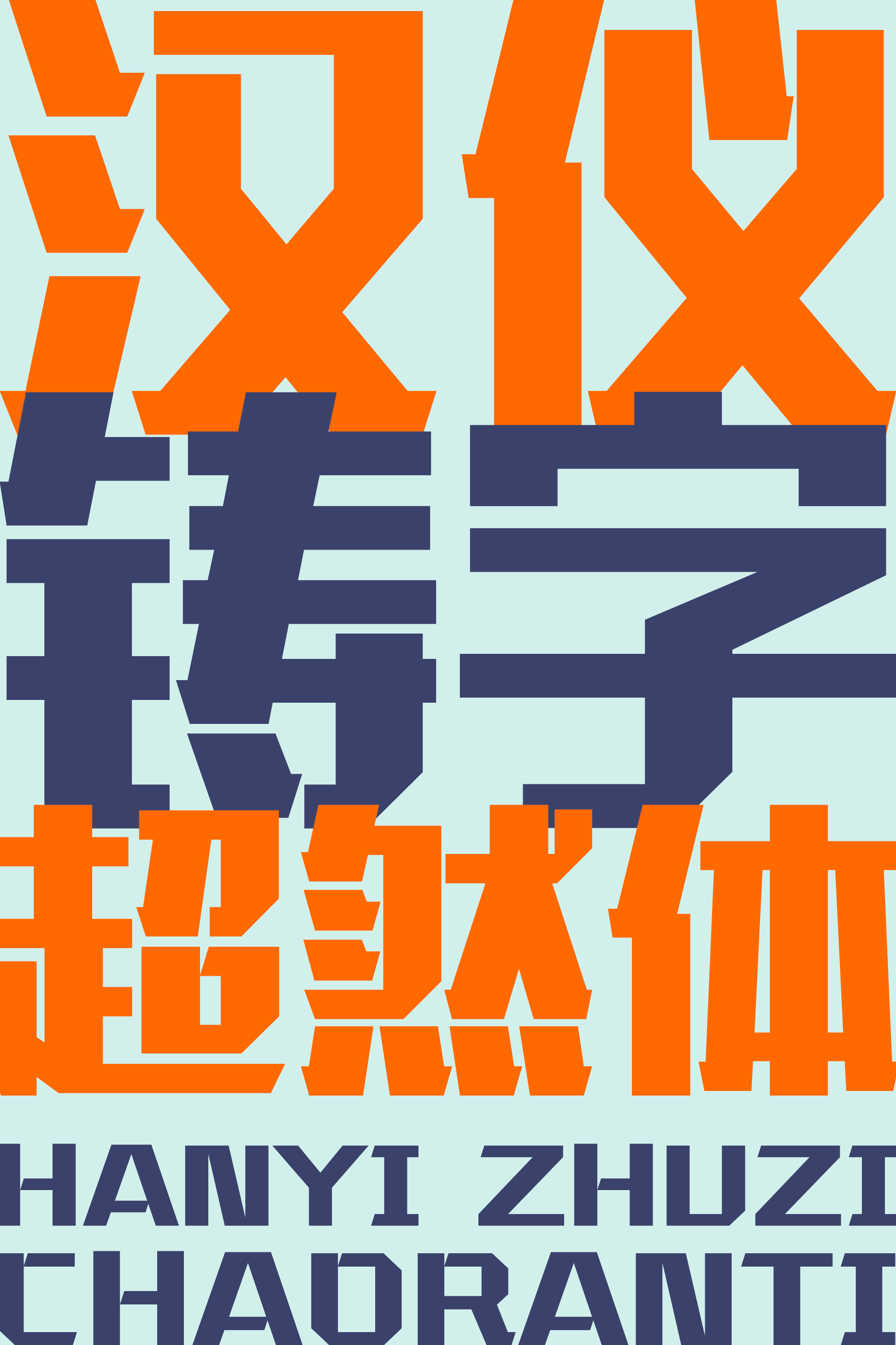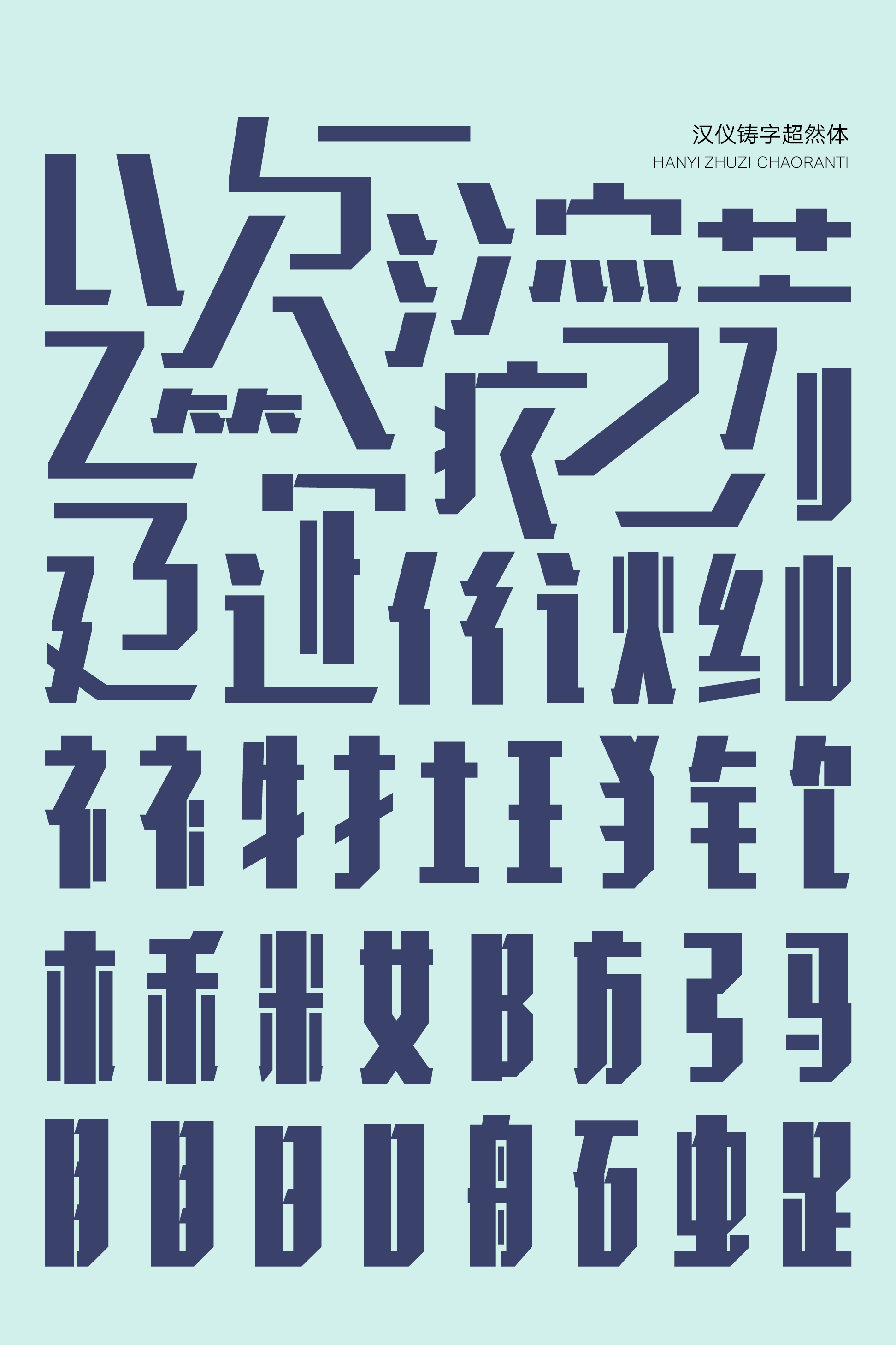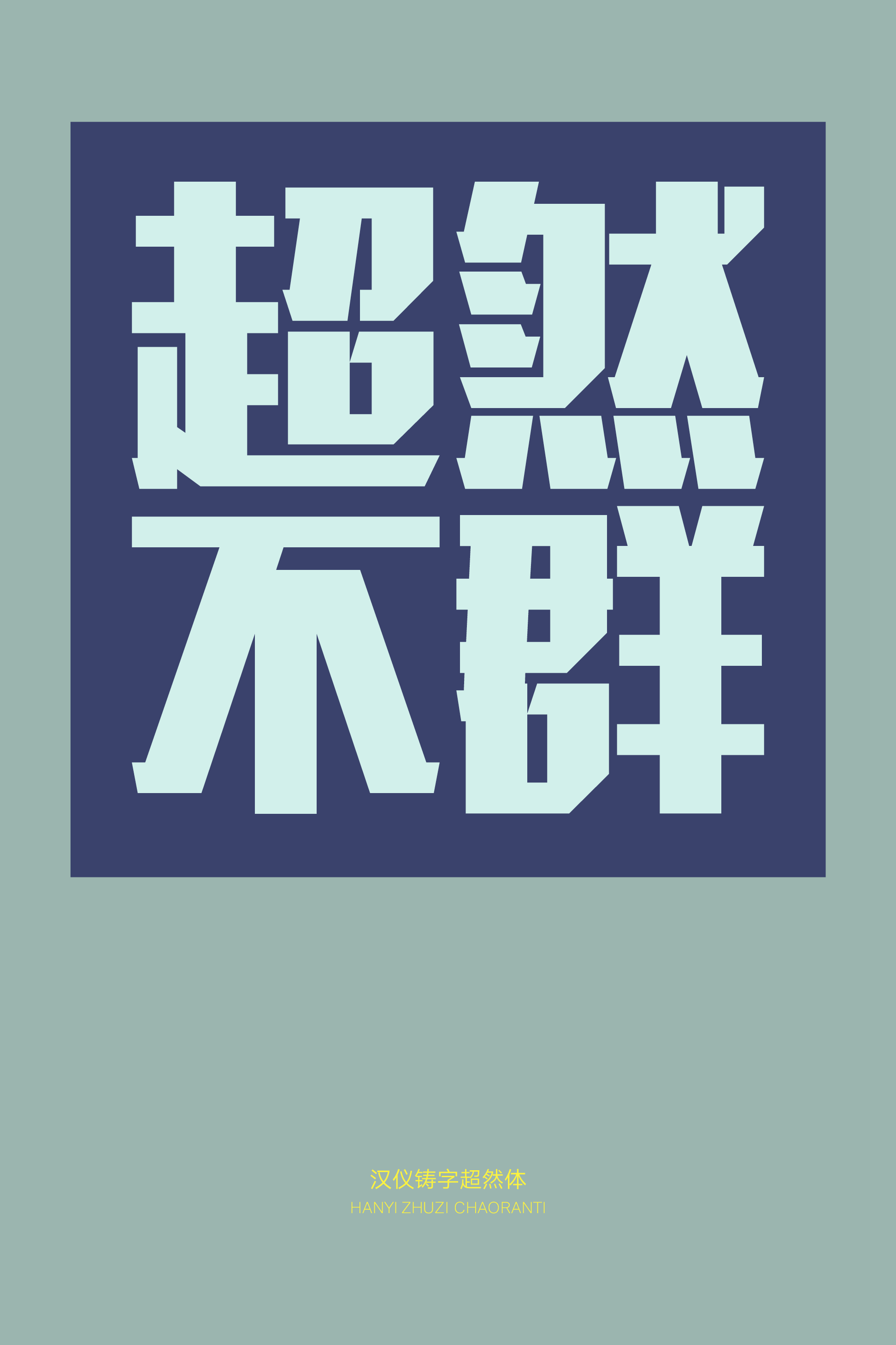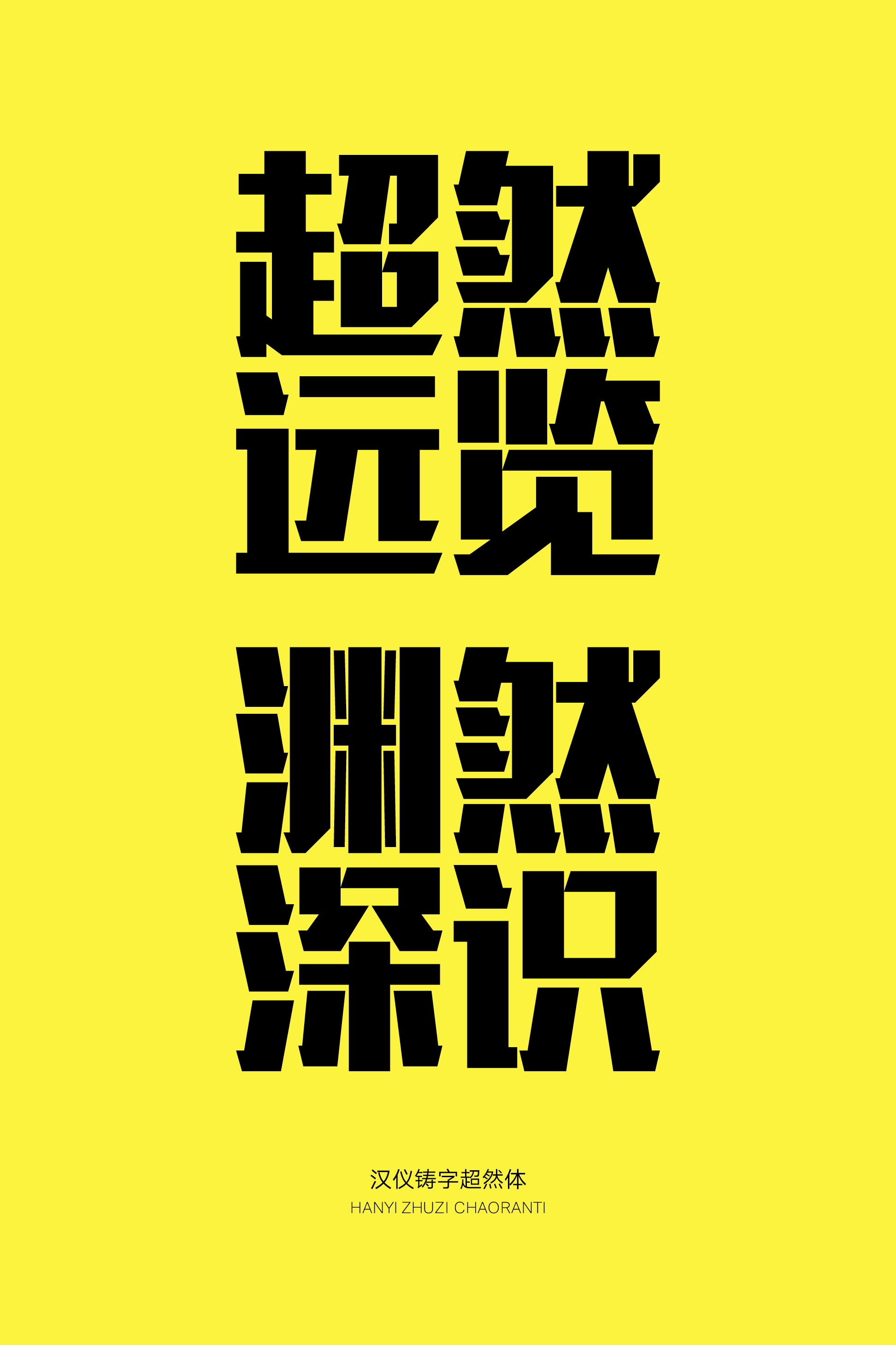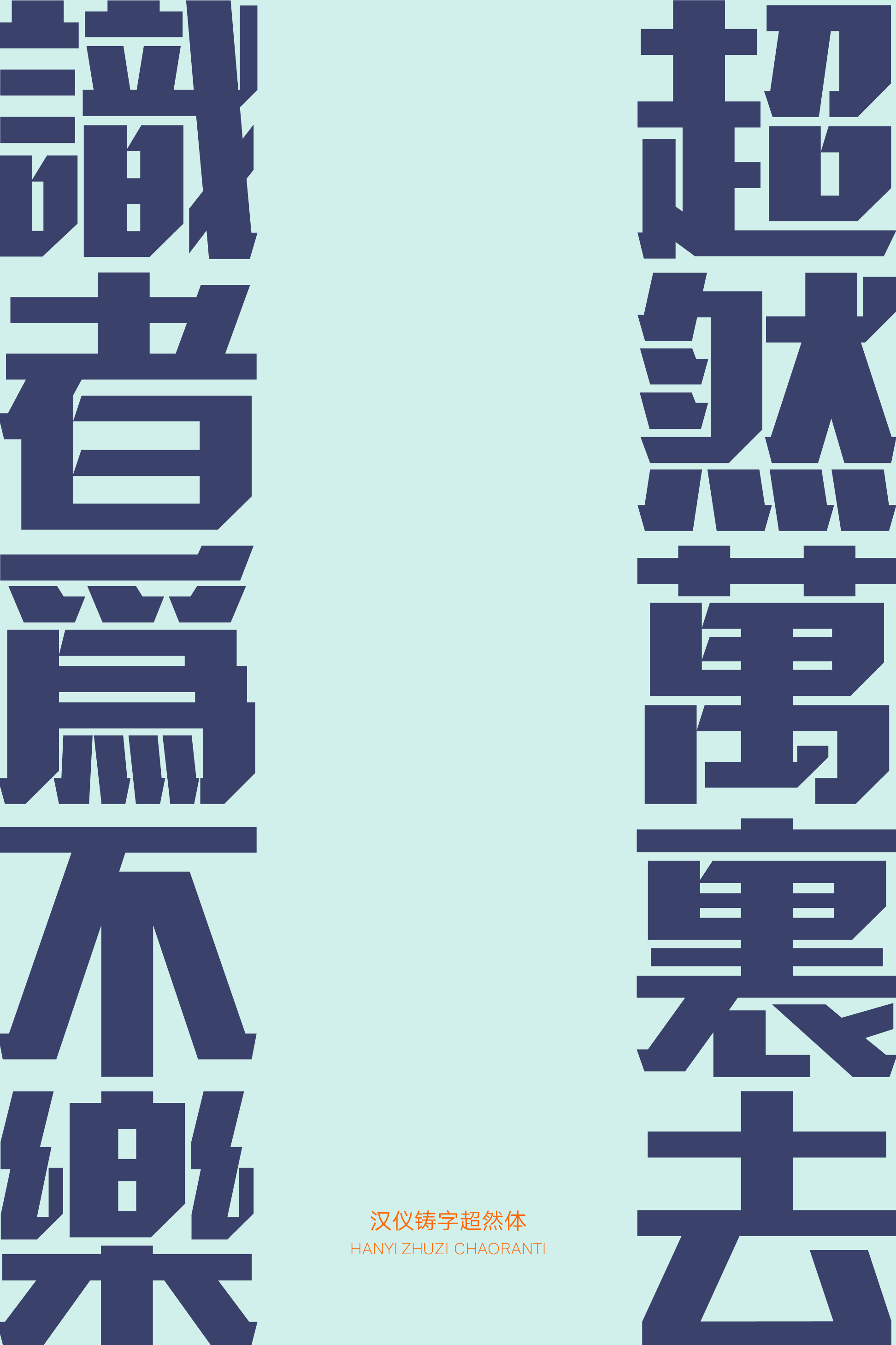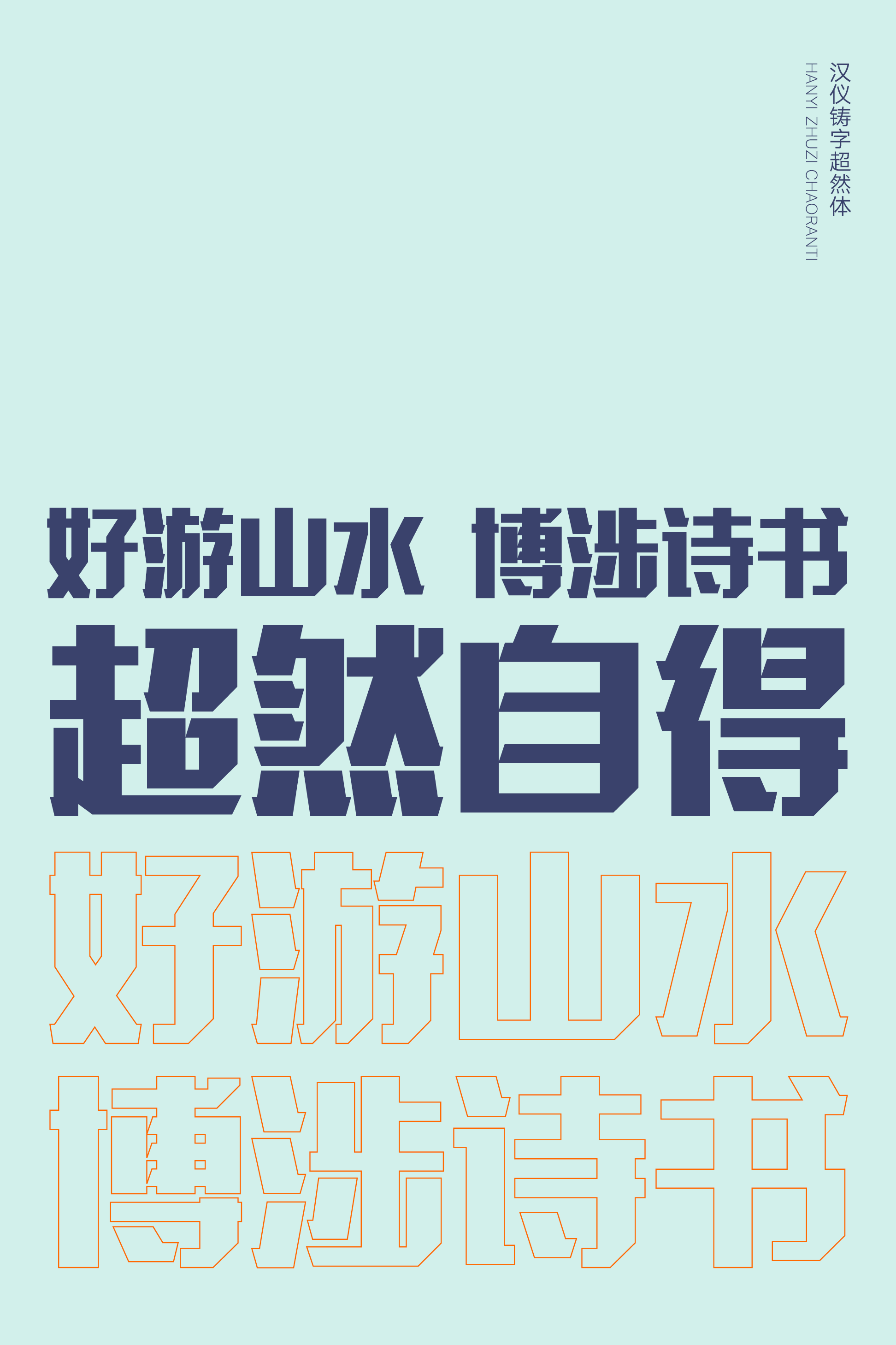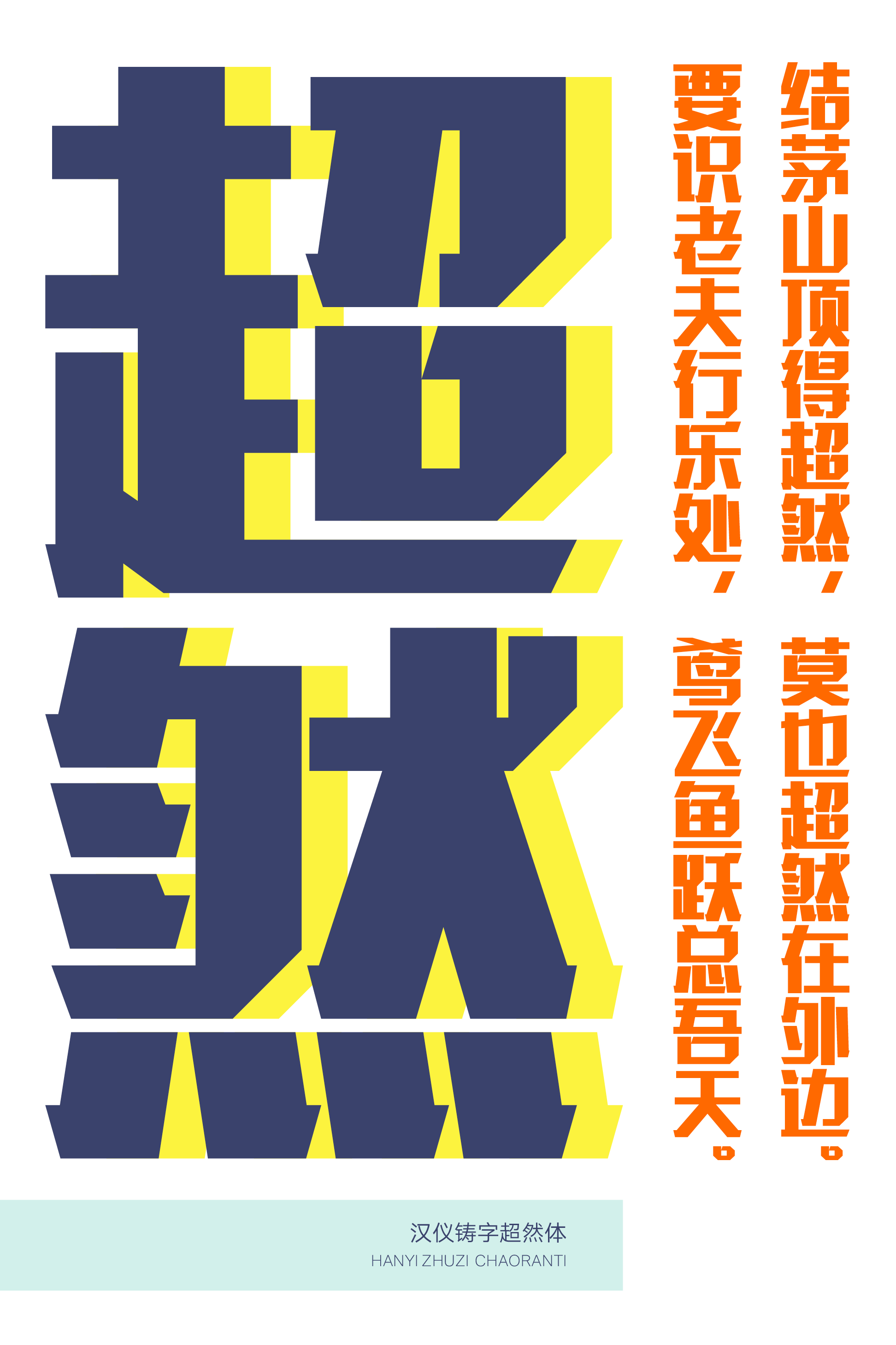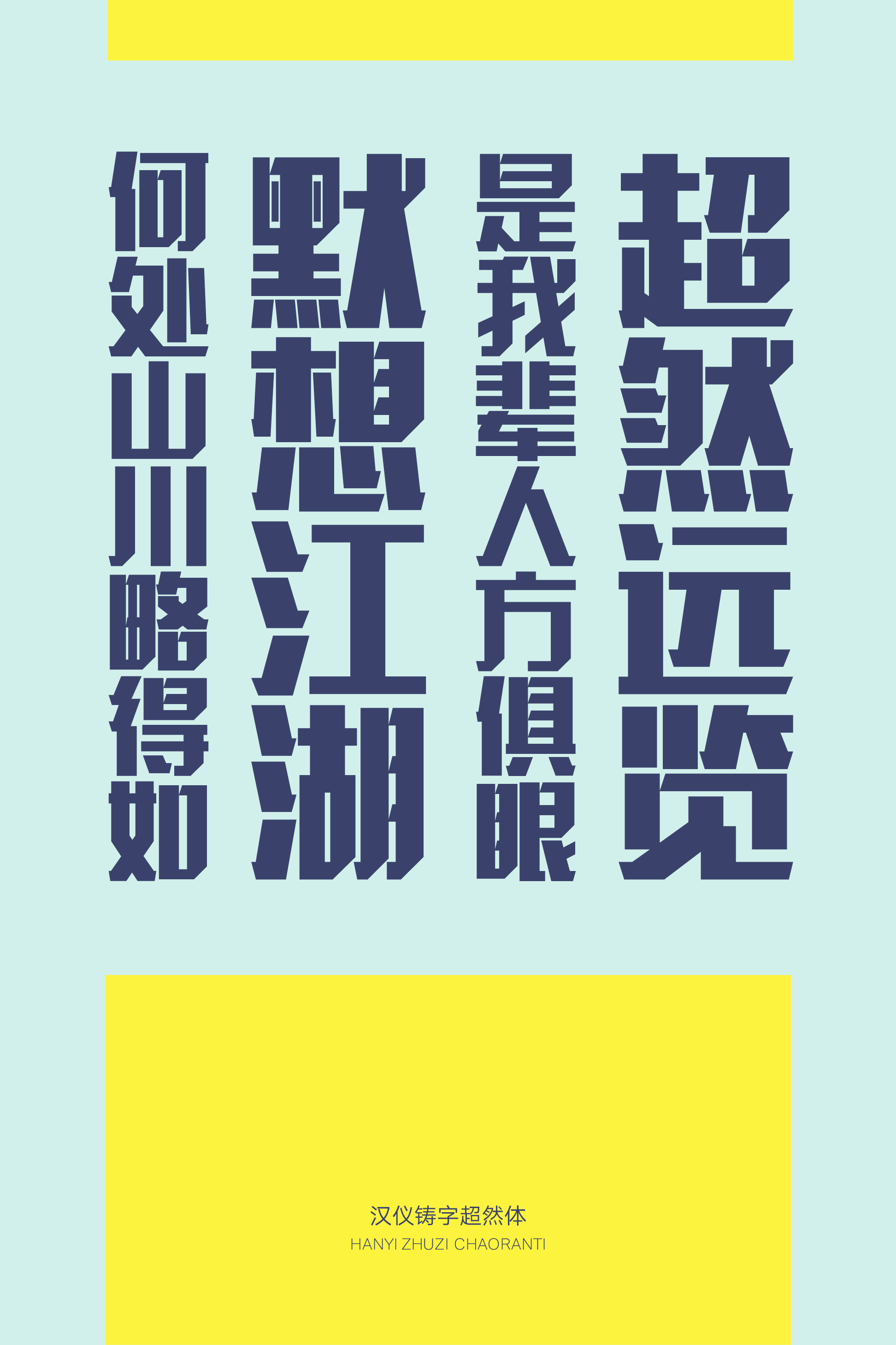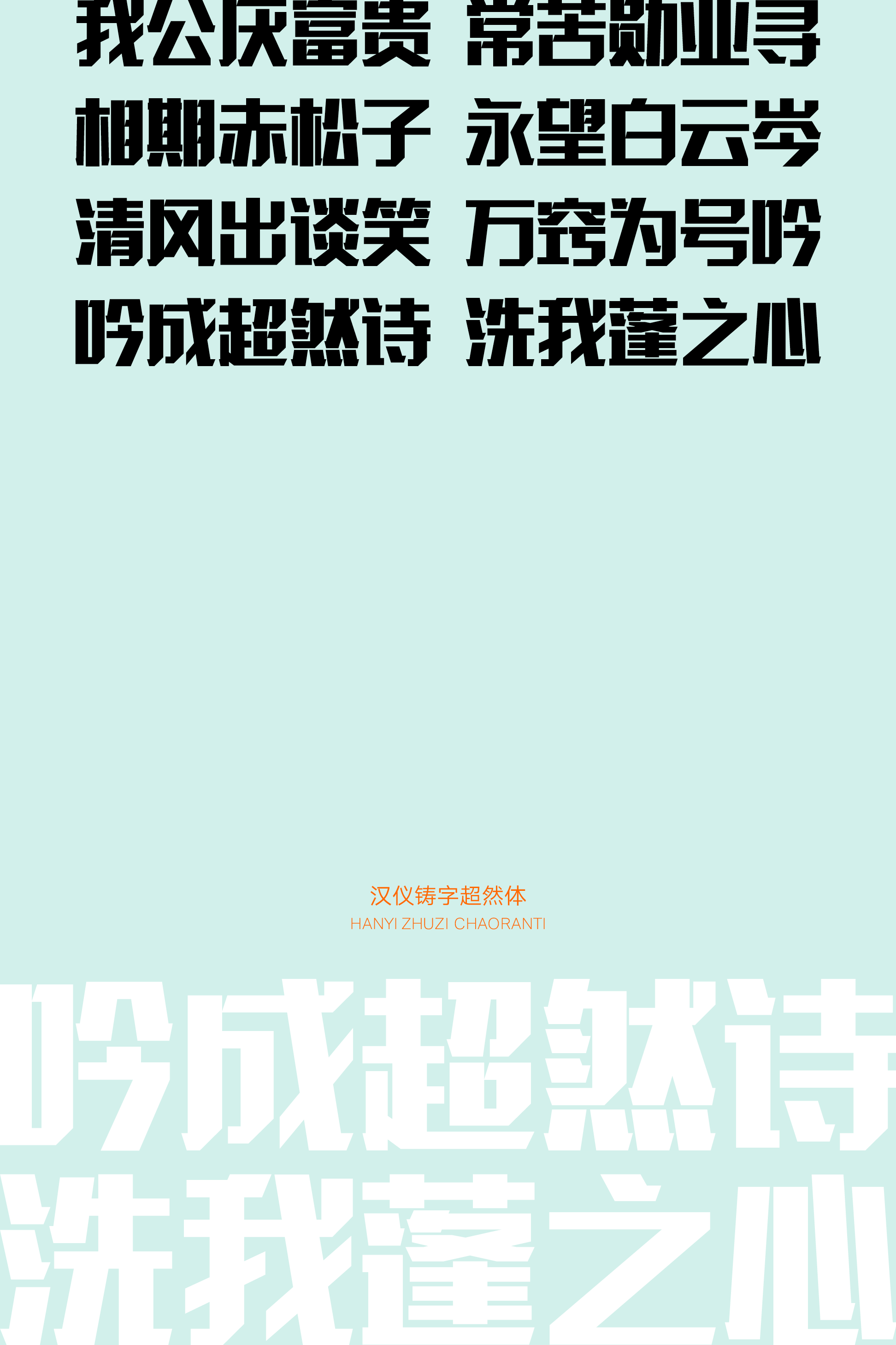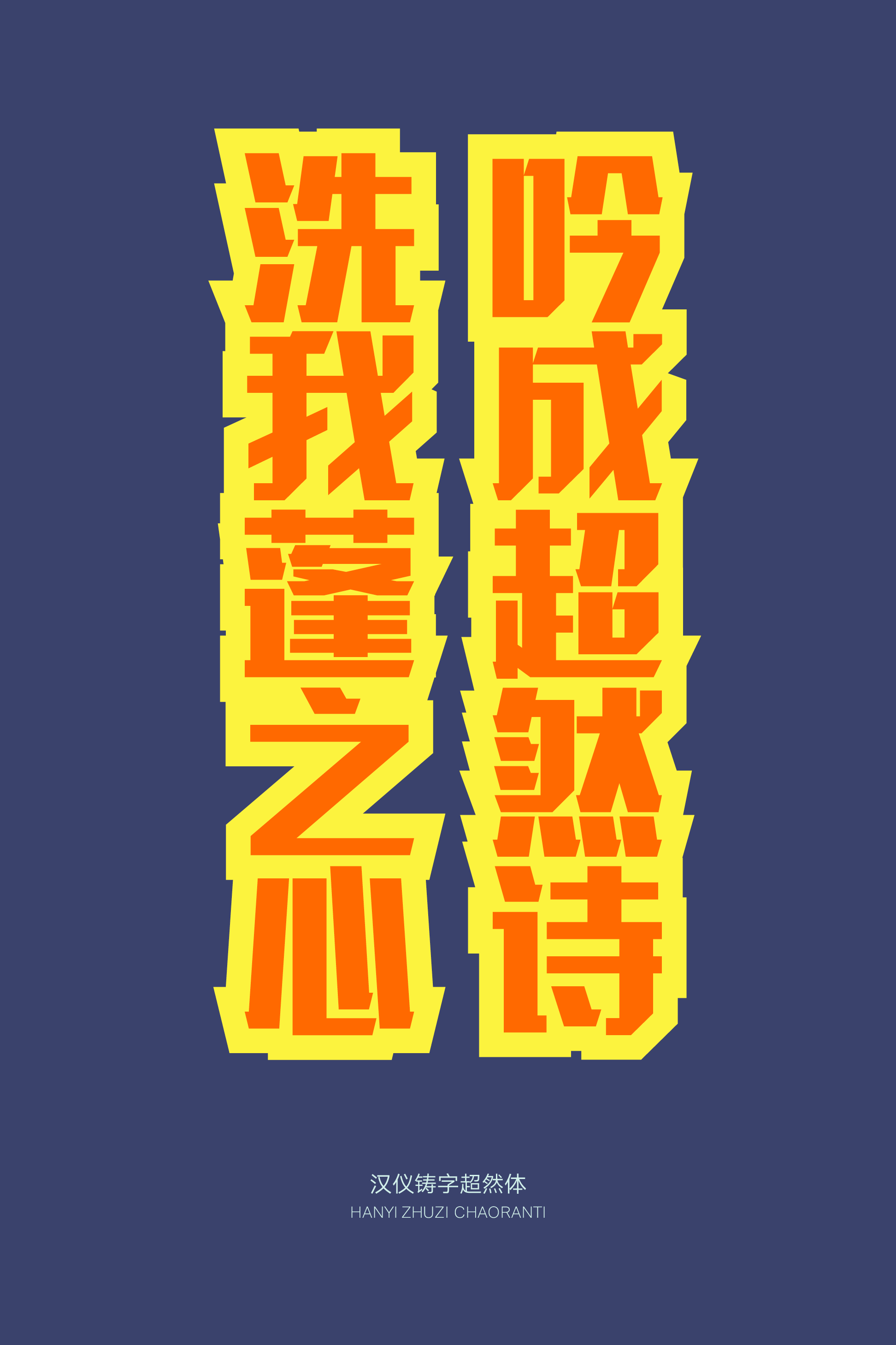
汉仪铸字超然体
汉仪铸字超然体,体现了速度与力量的美感,笔画横平竖直、横细竖粗、棱角分明。这款力量十足的标题美术字无论是在体育运动品牌的标识和包装、影视综艺节目的标题和花字,还是潮流电商的广告和海报,都可以大展身手,给人以强烈的视觉印象。
方块字形具有力量感,字面大而饱满。
笔画横平竖直,横细竖粗,横竖比例为1:2。
部分笔画采用切角处理,棱角分明。
西文部分延续了力量十足的方直造型,加入切角的细节处理,中西文匹配风格一致。